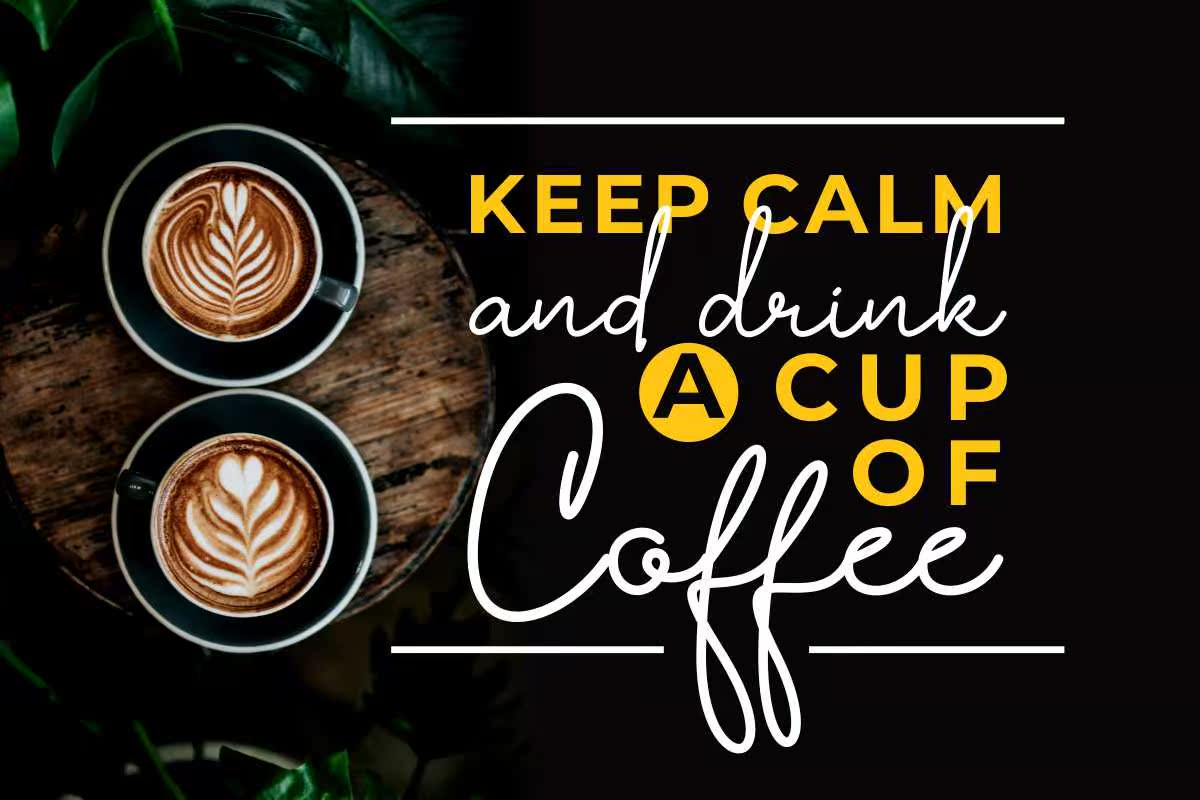
SmartJackisaneLegant、Modernhand和WrittenFont。它适用于您的创意项目,如徽标和品牌、婚礼宣传设计、产品包装、产品设计、标签、社交媒体、广告、摄影、水印、,以及任何需要手写风格的项目。SmartJackisaneLegant、Modern和WrittenFont。它适用于您的创意项目,包括徽标和品牌、婚礼宣传设计、产品包装、产品设计、标签、社交媒体、广告、摄影、水印以及任何需要手写风格的项目。